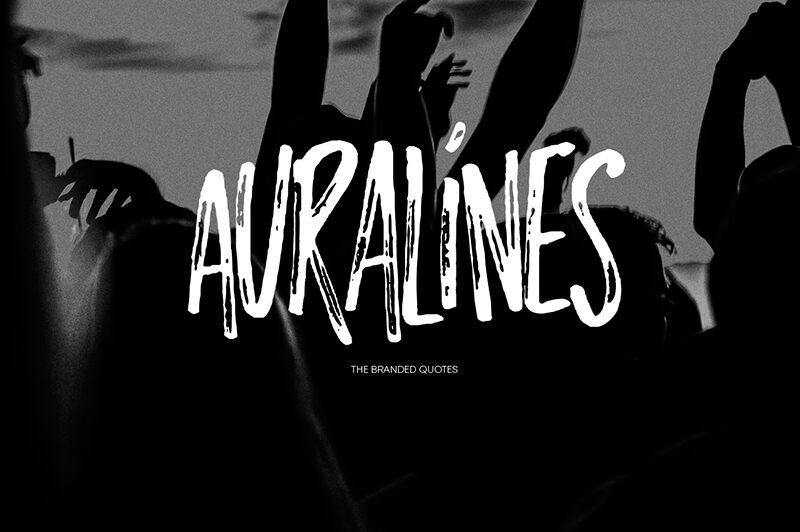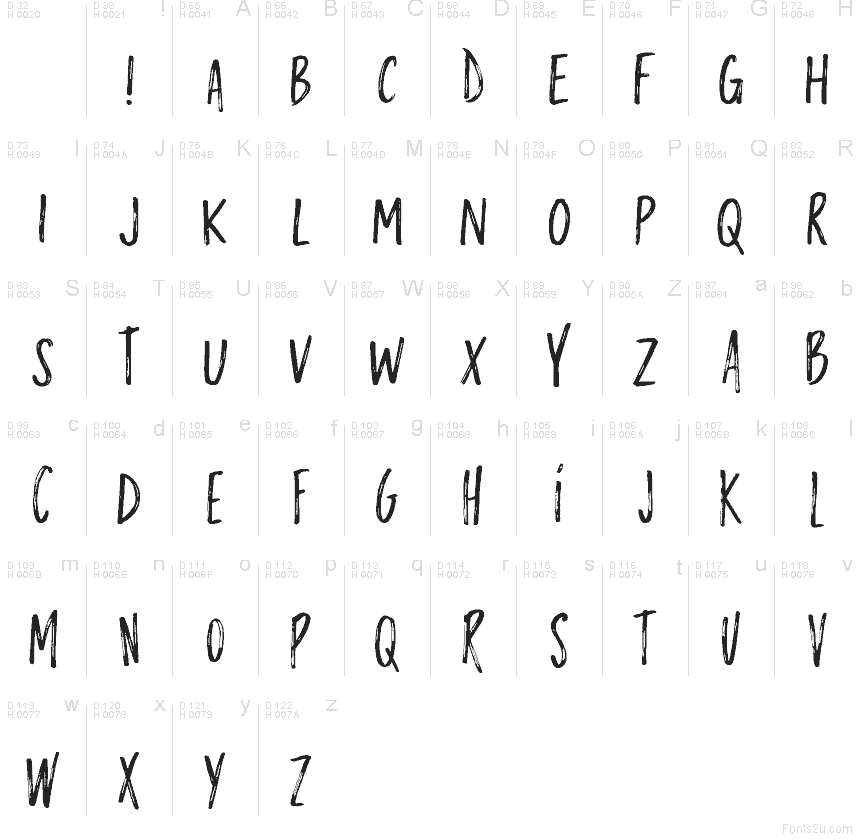
Auralines Demo
Auralines de The Branded Quotes es una tipografía gratuita de pincel seco (dry-brush) en mayúsculas, con ese ritmo crudo propio de la pintura a mano. Las letras son altas, estrechas y tienen un aire inquieto; sus trazos deshilachados, bordes irregulares y cortes diagonales rápidos dan la impresión de tinta arrastrada velozmente sobre una superficie rugosa.
Encaja a la perfección en carteles de música, gráficos de streetwear, portadas de zines, títulos y packaging llamativo, donde hace falta una tipografía gratuita con más personalidad que pulido. Como sus mayúsculas son esbeltas y dinámicas en lugar de pesadas, también funciona muy bien para titulares breves, nombres de artistas y monogramas que busquen ese pulso rápido y artesanal.